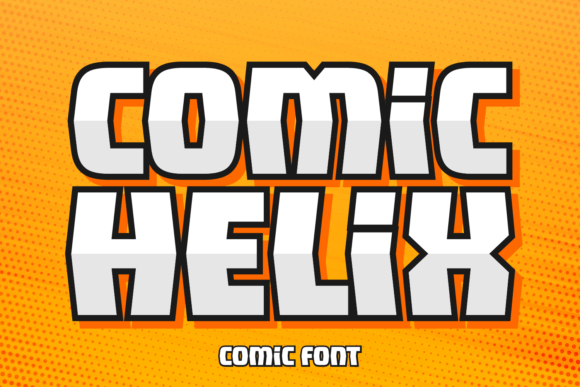
Comic Helix
適切なデザイン要素を見つけるのは難しい場合がありますが、Comic Helixは作品を即座に引き立てる優れたコレクションを提供します。
POD(オンデマンド印刷)製品、結婚式の招待状、またはソーシャルメディアのグラフィックを作成している場合でも、Comic Helixは理想的です。